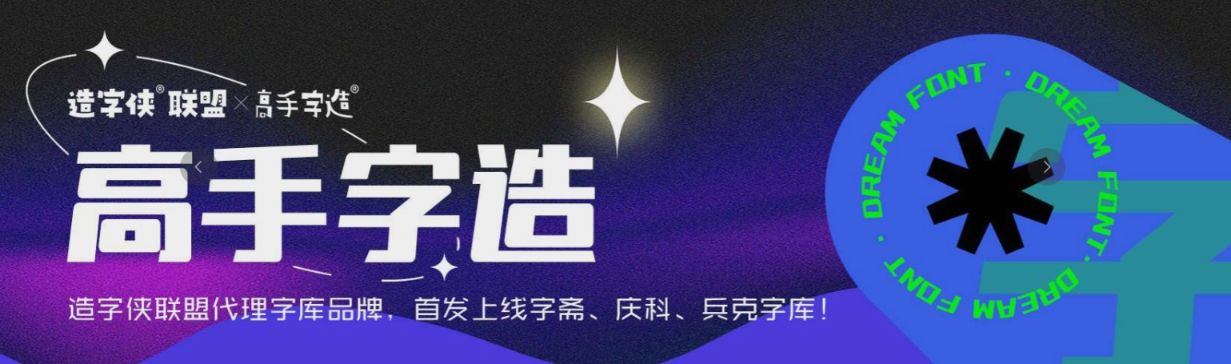
更多字体选择!首发上线字斋、庆科、兵克字库!
随着设计的多元化,字体的选择在品牌塑造和用户体验中起着越来越重要的作用。为了满足大家对字体的不同需求,励字造梦字库,首发上线字斋、庆科、兵克字库!
我们推出了首发上线的字斋、庆科和兵克字库,旨在提供更多样化的字体选择,帮助设计师打造独具特色的作品。
字斋字库
字斋字库专注于为设计师提供精致、优美的中文字体。该字库收录了大量具有艺术感的字体,如手写体、仿宋体等,适用于品牌形象设计、海报制作、书籍排版等领域。字斋字库的字体风格独特,能够为设计师提供丰富的创意灵感,满足各种设计需求。
庆科字库
庆科字库则以科技感和未来感为主打,收录了一系列具有前卫风格的字体。这些字体线条流畅、结构简洁,非常适合用在数字界面、科幻主题的设计中。庆科字库的字体不仅具有视觉冲击力,还能为品牌塑造出独特的科技形象。
兵克字库
兵克字库则注重实用性和易用性,收录了大量适用于印刷品、网站、APP等不同媒介的字体。这些字体设计简洁、易于辨识,能够满足大多数设计项目的需求。兵克字库还提供多种语言支持,如英文、阿拉伯文等,为全球范围内的设计项目提供全面的字体解决方案。
三个首发上线的字库各具特色,能够满足不同设计领域的需求。无论是需要精美艺术感的品牌形象设计,还是追求科技感和未来感的数字界面设计,或者是重视实用性和易用性的印刷品、网站设计,都能在这些新上线的字库中找到合适的字体。同时,我们也欢迎广大设计师和字体爱好者提供宝贵意见和建议,共同推动字体设计的创新和发展。